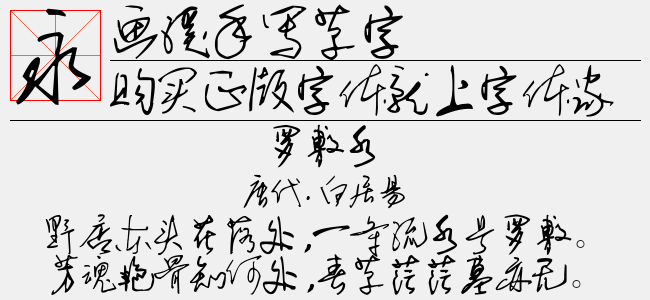
画溪手写草字(2.03 MTTF中文字体下载)
画溪手写草字 字体大小2.03 M,包含了6763个汉字以及附加其他英文字体和阿拉伯数字,属于佚名。画溪手写草字(TTF)可以免费下载,商业用途请自行购买版权,它的特征就是手写,草书,手书风格,书法,采用安装嵌入的安装方式,支持符号拉丁文日文中文等语言
字体名称:画溪手写草字